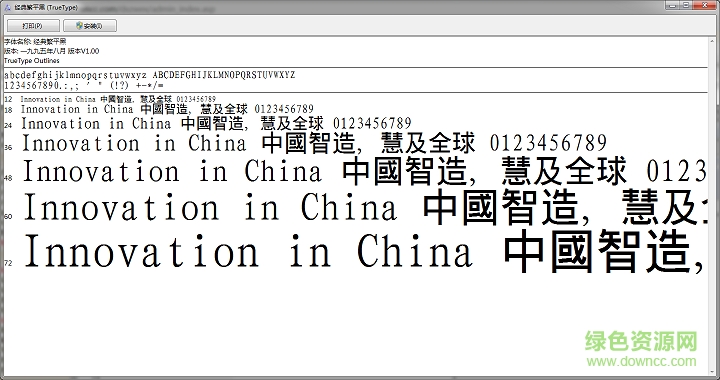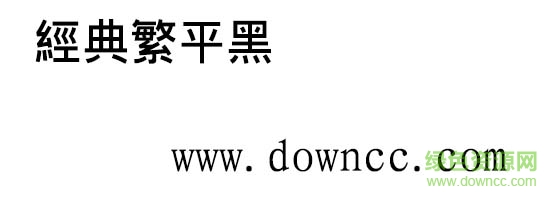
1.中國(guó)的字體設(shè)計(jì)是在印刷術(shù)的產(chǎn)生和發(fā)展中應(yīng)運(yùn)而生的。在古代,中國(guó)的字體設(shè)計(jì)曾有過(guò)輝煌的歷史時(shí)期,在宋朝時(shí)進(jìn)入黃金時(shí)代。
2.清朝末年,鉛字排版印刷術(shù)傳入中國(guó),字體設(shè)計(jì)進(jìn)入鉛字時(shí)代。這個(gè)時(shí)期的字體設(shè)計(jì)既要帶有傳統(tǒng)文化的審美慣性,又要符合鉛字印刷的工藝要求,字體設(shè)計(jì)走到了轉(zhuǎn)折的關(guān)口。
3.鉛字印刷是印刷走入機(jī)械化、工業(yè)化時(shí)代的標(biāo)志,但在這一時(shí)代里,印刷字體設(shè)計(jì)卻始終無(wú)法超越手工勞動(dòng)的制約,無(wú)法擺脫刻模、鑄字、撿字、排版等一系列印前繁雜工藝的束縛